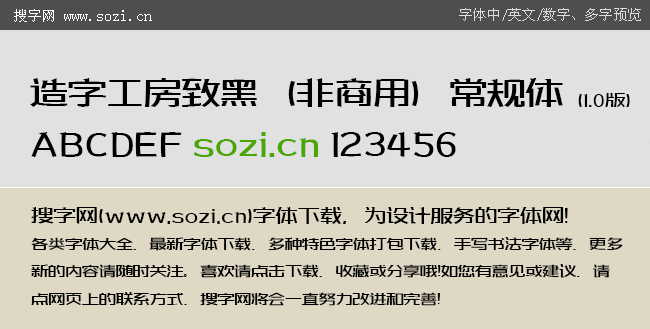
造字工房致黑體
搜字網(wǎng)提供一款造字工房致黑體中文藝術(shù)字體下載,造字工房致黑體字形結(jié)構(gòu)嚴(yán)謹(jǐn)而疏朗、形疏而氣緊,橫平豎直的筆畫中加入弧度的處理,剛正而不失盈潤(rùn),局部筆畫加入了尖突的效果,讓字形更顯英朗氣質(zhì)。此款字體適用于報(bào)刊雜志及書籍、畫報(bào)的主副標(biāo)題和個(gè)性品牌設(shè)計(jì)推廣等環(huán)境。